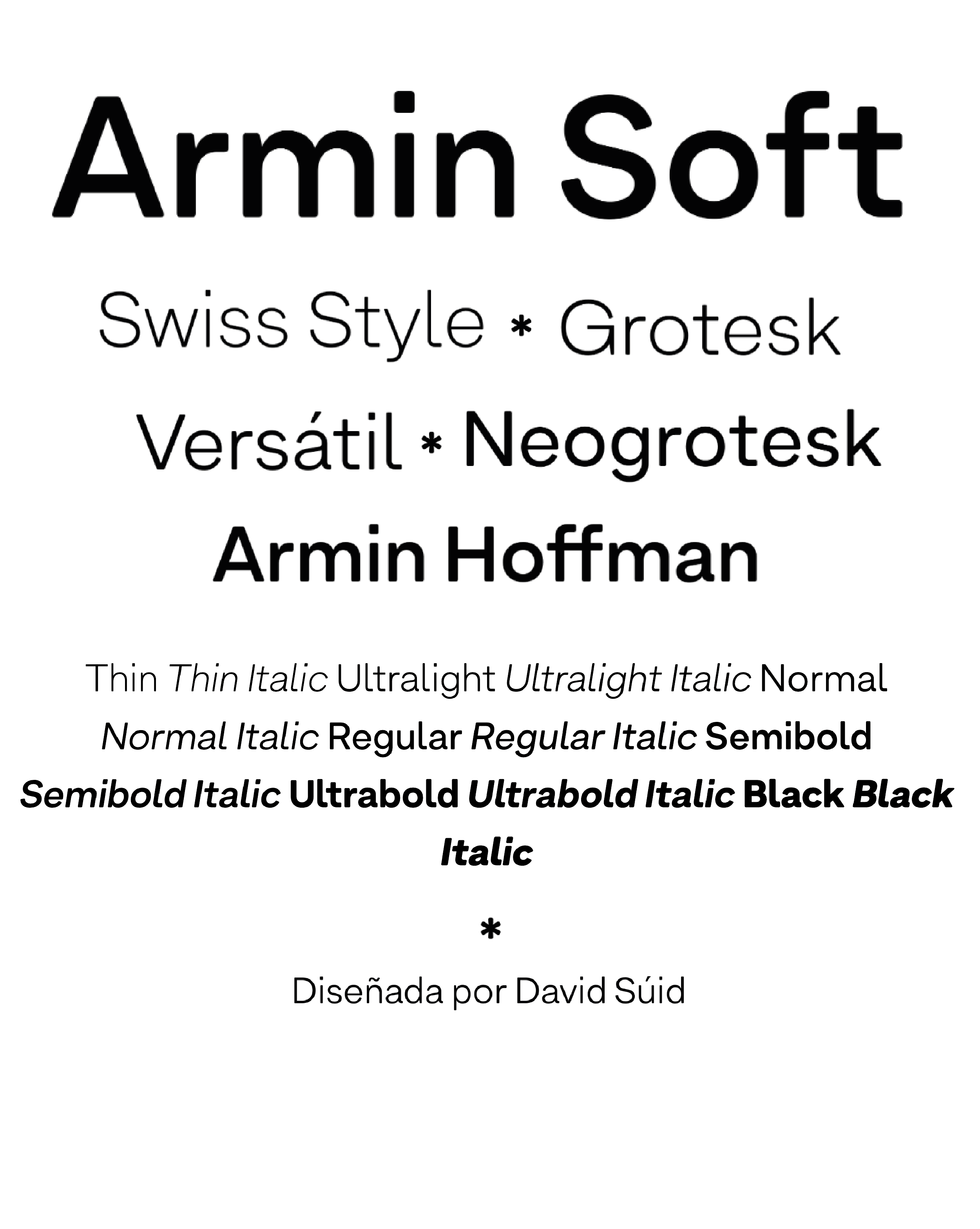
| Año | 2020 |
| Créditos | David Súid |
| Descripción | Las tipografías grotesk y neo-grotesk son una parte fundamental de las herramientas que hacen posible esta estética. Un lenguaje visual que nos ha generado plena admiración desde que éramos estudiantes. |
| Clasificación | Texto |
| Familia(s) | Armin Grotesk, Armin Soft Thin, Armin Soft Thin Italic, Armin Soft Ultralight, Armin Soft Ultralight Italic, Armin Soft Normal, Armin Soft Normal Italic, Armin Soft Regular, Armin Soft Regular Italic, Armin Soft Semibold, Armin Soft Semibold Italic, Armin Soft Ultrabold, Armin Soft Ultrabold Italic, Armin Soft Black, Armin Soft Black Italic |
| Estilos | 14 |
| Fundidora | W Type Foundry |